Rob Stenson, 2023
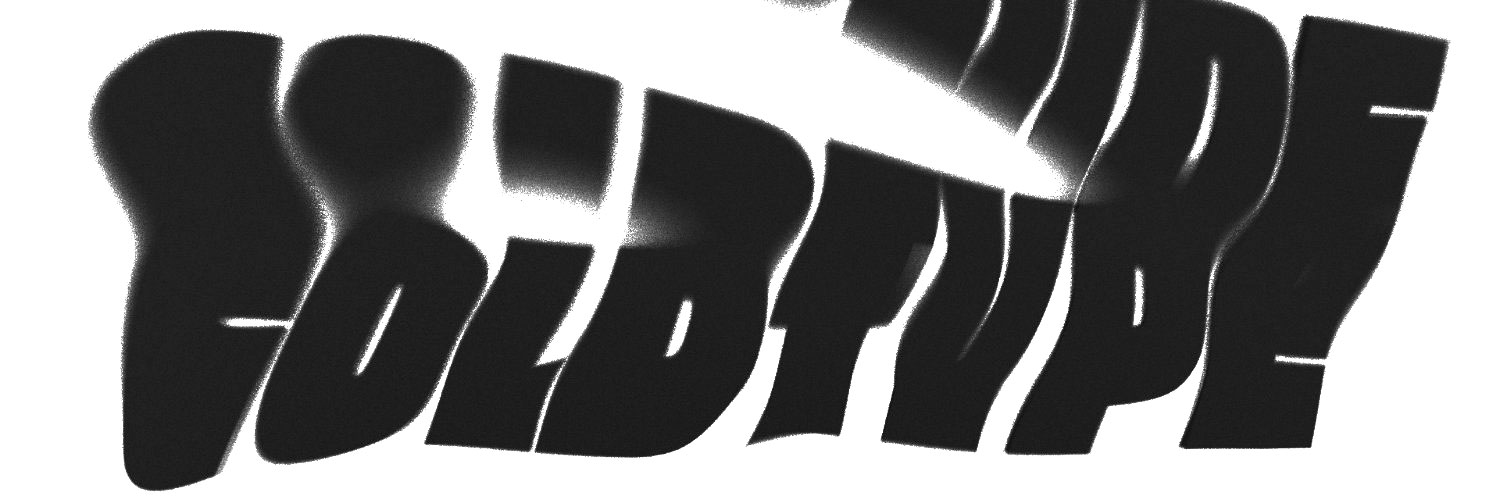
Relevancia
Este trabajo se centra en el desarrollo de Coldtype, una librería de código abierto en Python para la composición y animación tipográfica mediante programación. El sistema está diseñado para explorar la relación entre la tipografía y la música.
Su principal aportación es la creación de una herramienta especializada que permite definir con código las relaciones entre parámetros sonoros (como datos MIDI) y los ejes de variación de una fuente. Esto posibilita que los tipos funcionen, en palabras de su creador, como instrumentos de percusión.
La relevancia de este proyecto es tanto técnica como conceptual, al proporcionar una metodología y un software específico para investigar las correspondencias entre la tipografía y el sonido, estableciendo un nuevo modelo para la creación de identidades sonoras y visuales interactivas.
Clasificación
- Década: Década de 2020
- Función: Exploración formal y/o performativa
- Contexto: Investigación / Experimental
- Grado de interactividad: Interacción débil o reactiva
- Input multimodal: No
- Tipo de input: Sonido
- Tipo de output: Transformación morfológica, Transformación espacial
- Tecnología empleada: Python, Desarrollo de la biblioteca Coldtype para animar tipografía (incluyendo tipografía variable) con sonido
- Alfanumérica: Sí
- Mantiene codificación textual: No